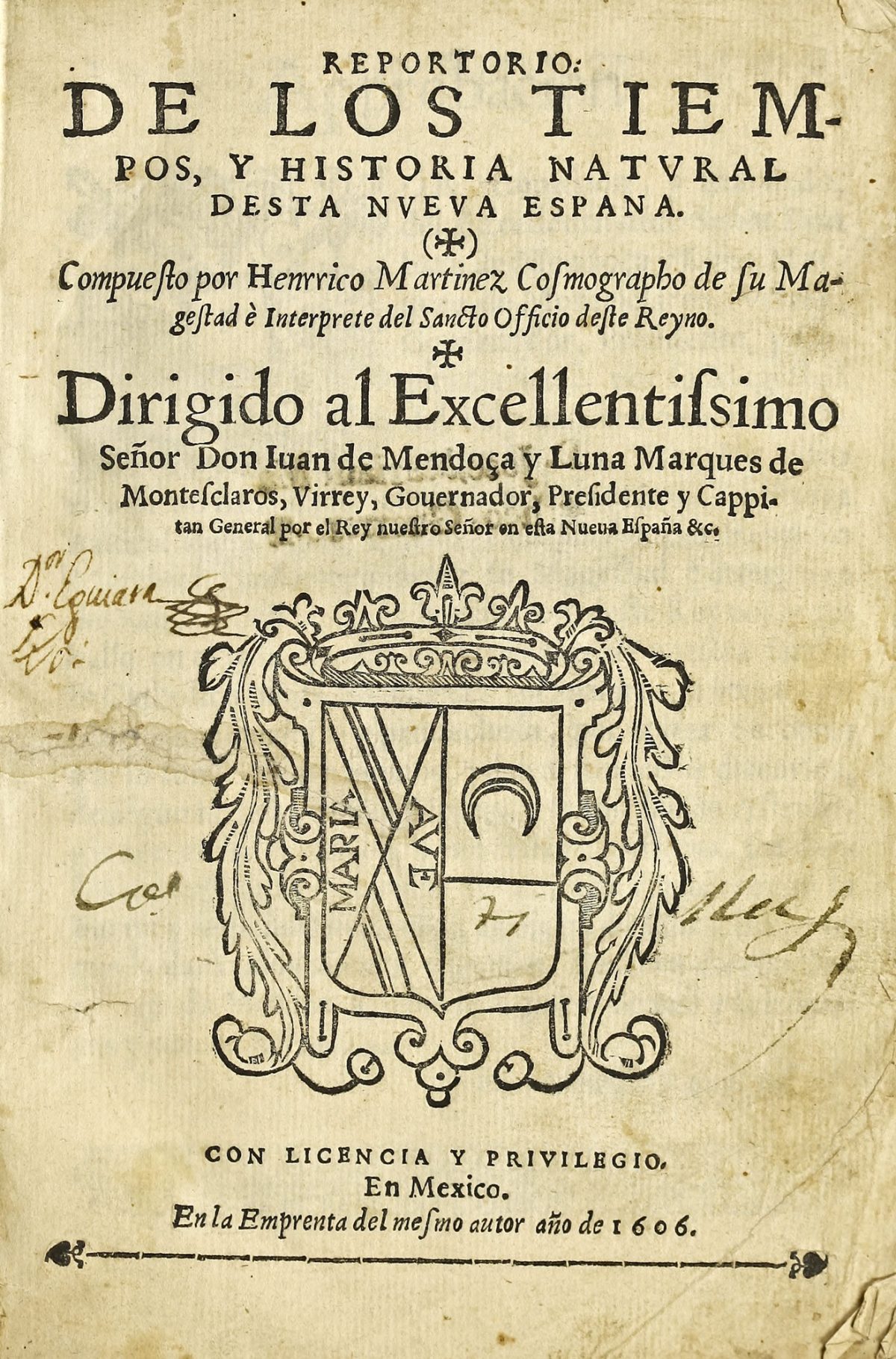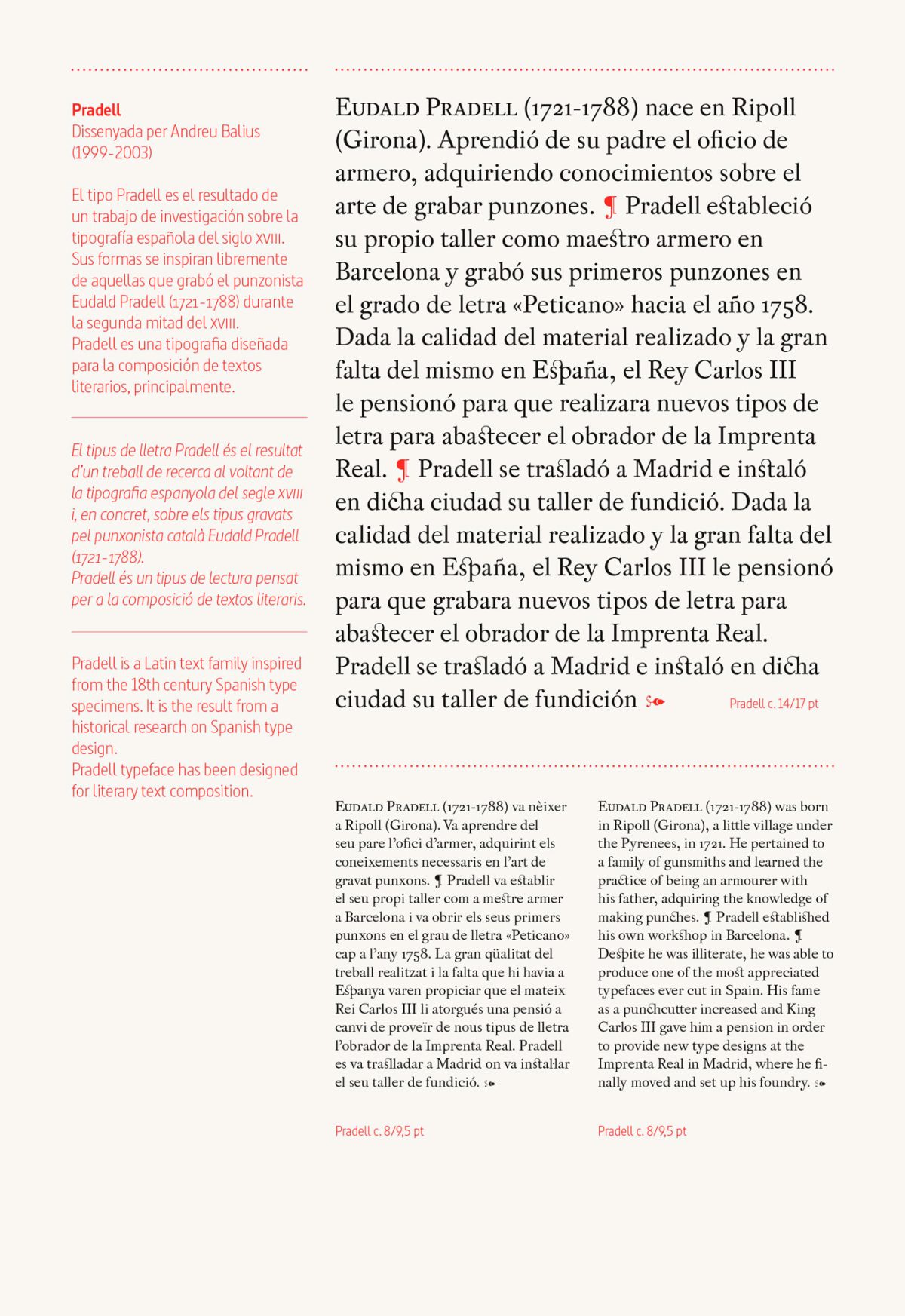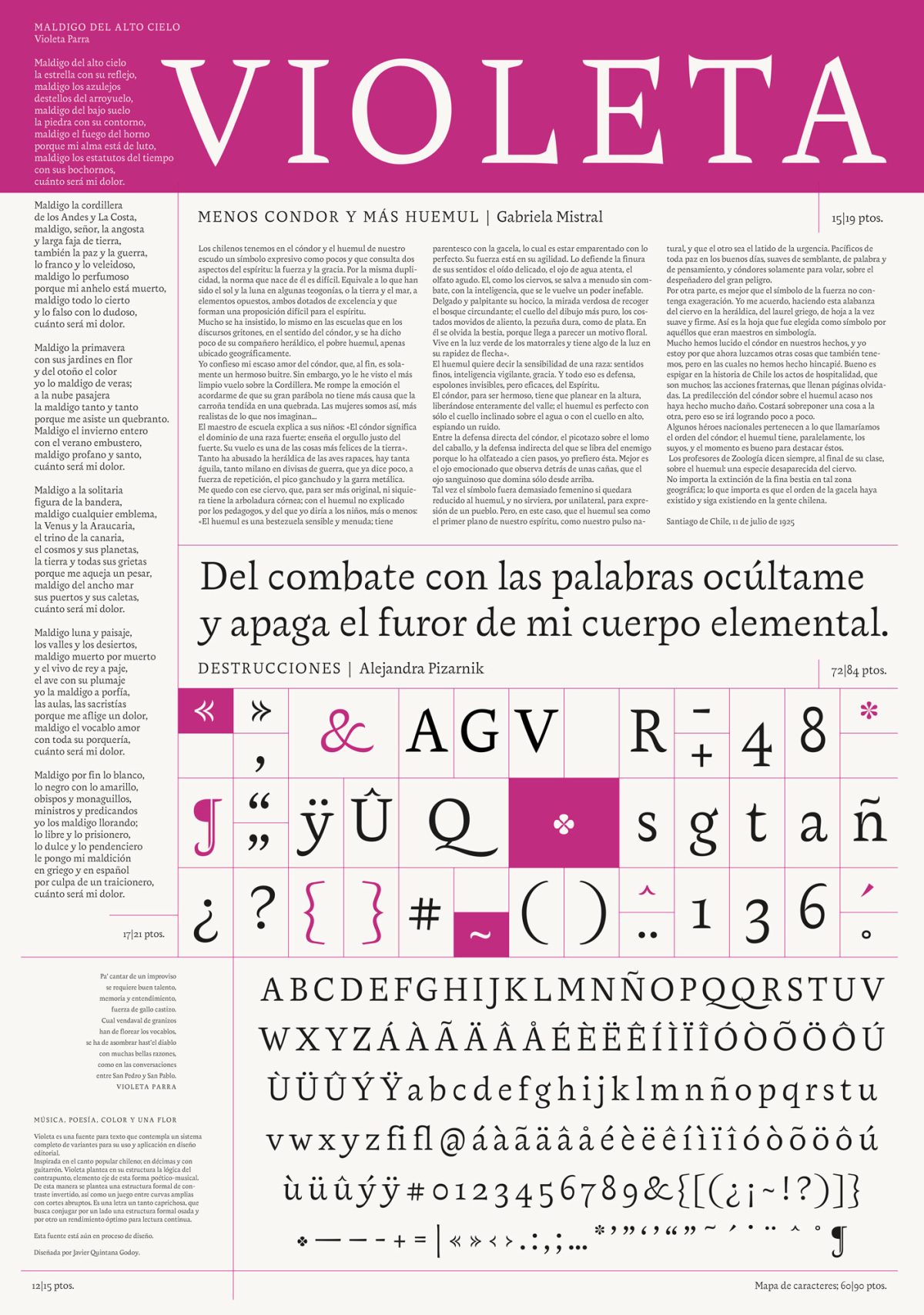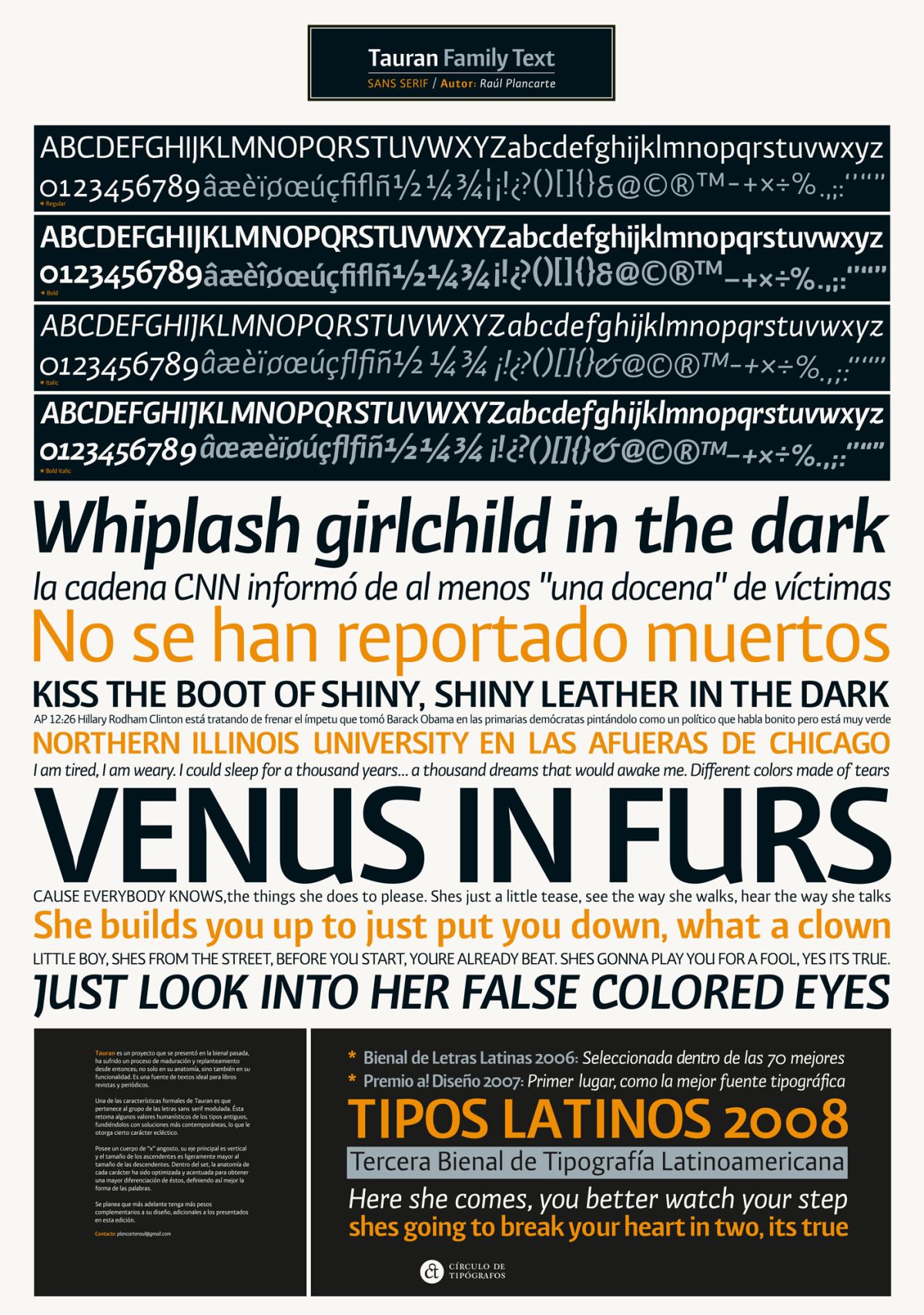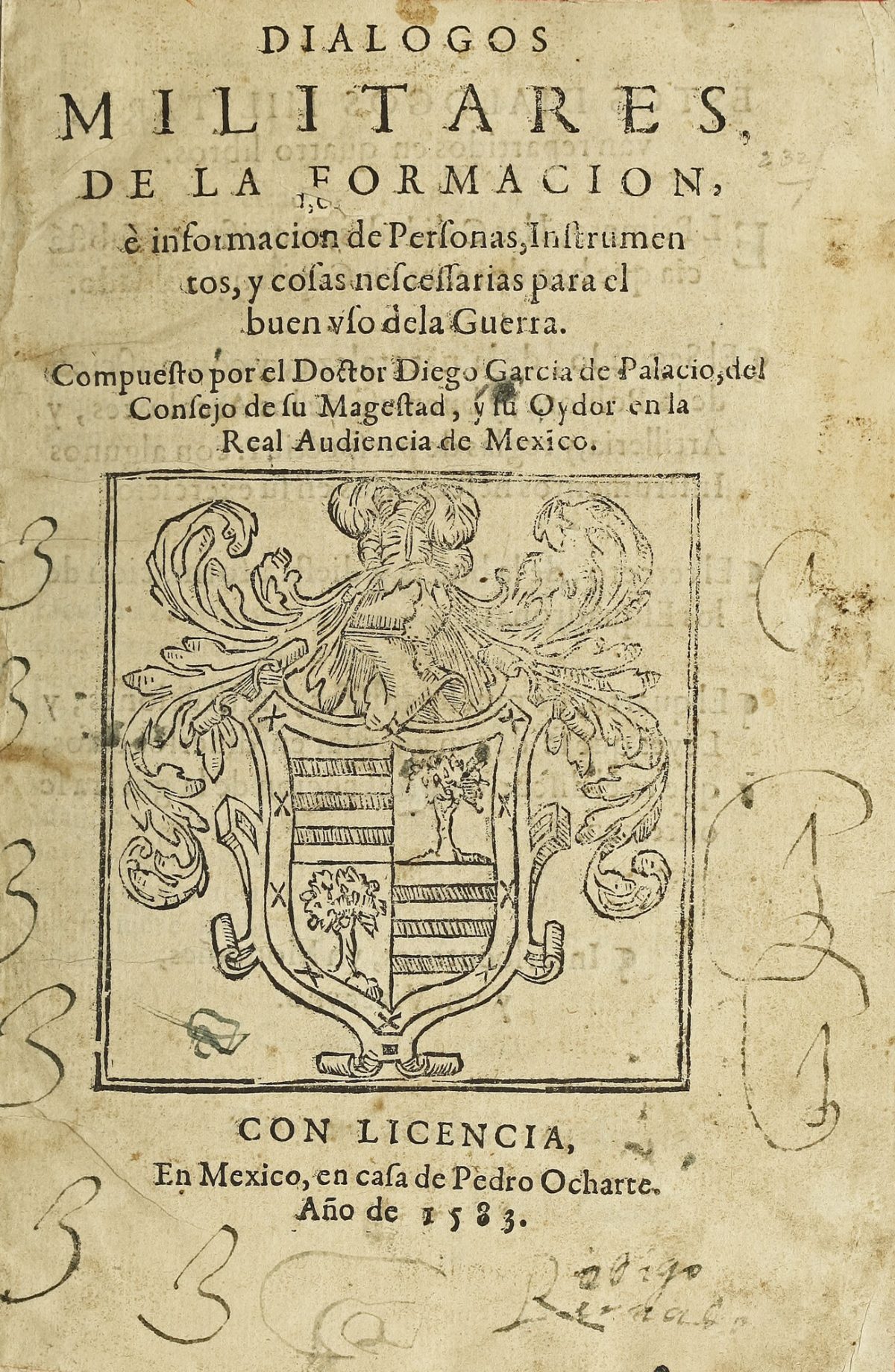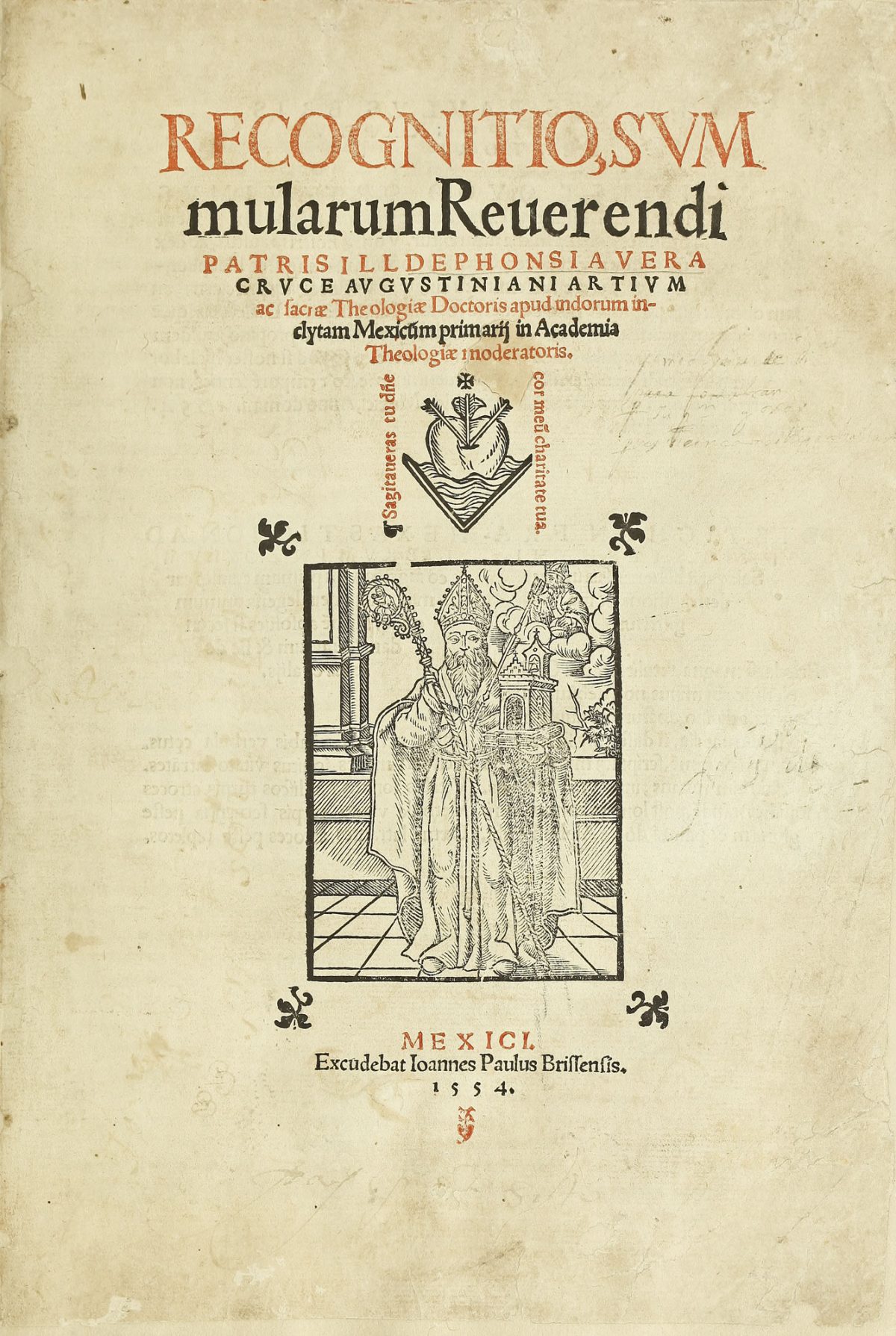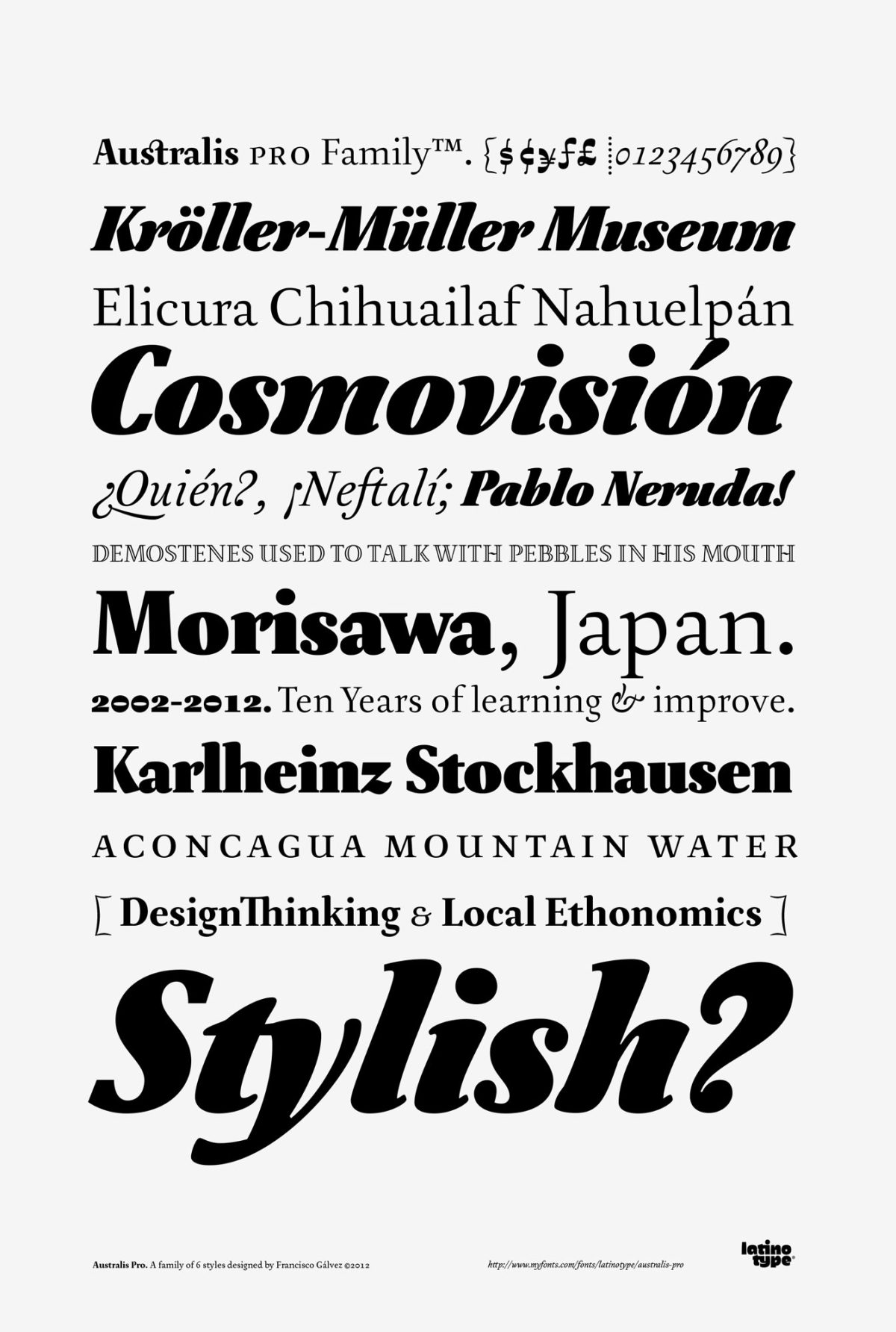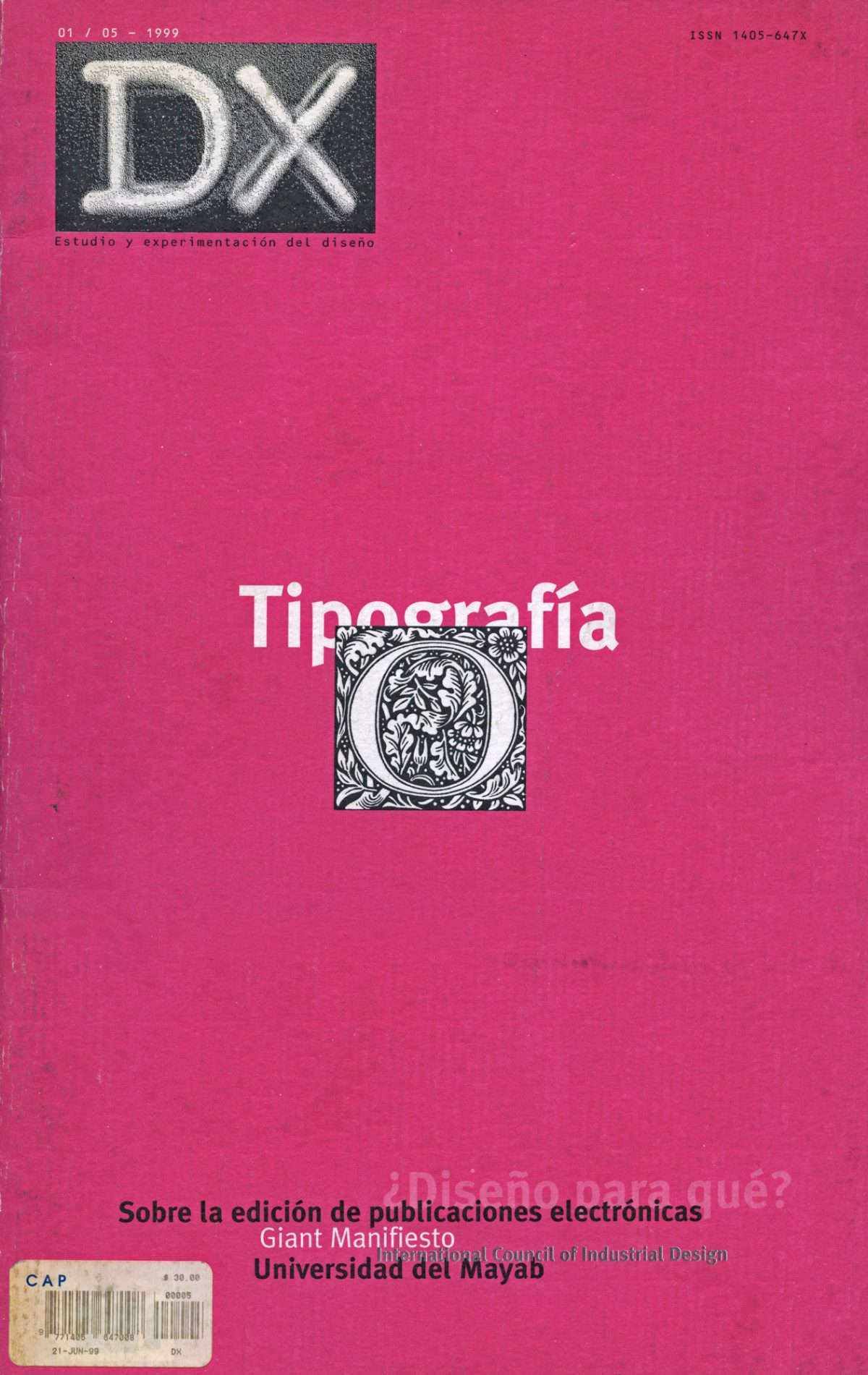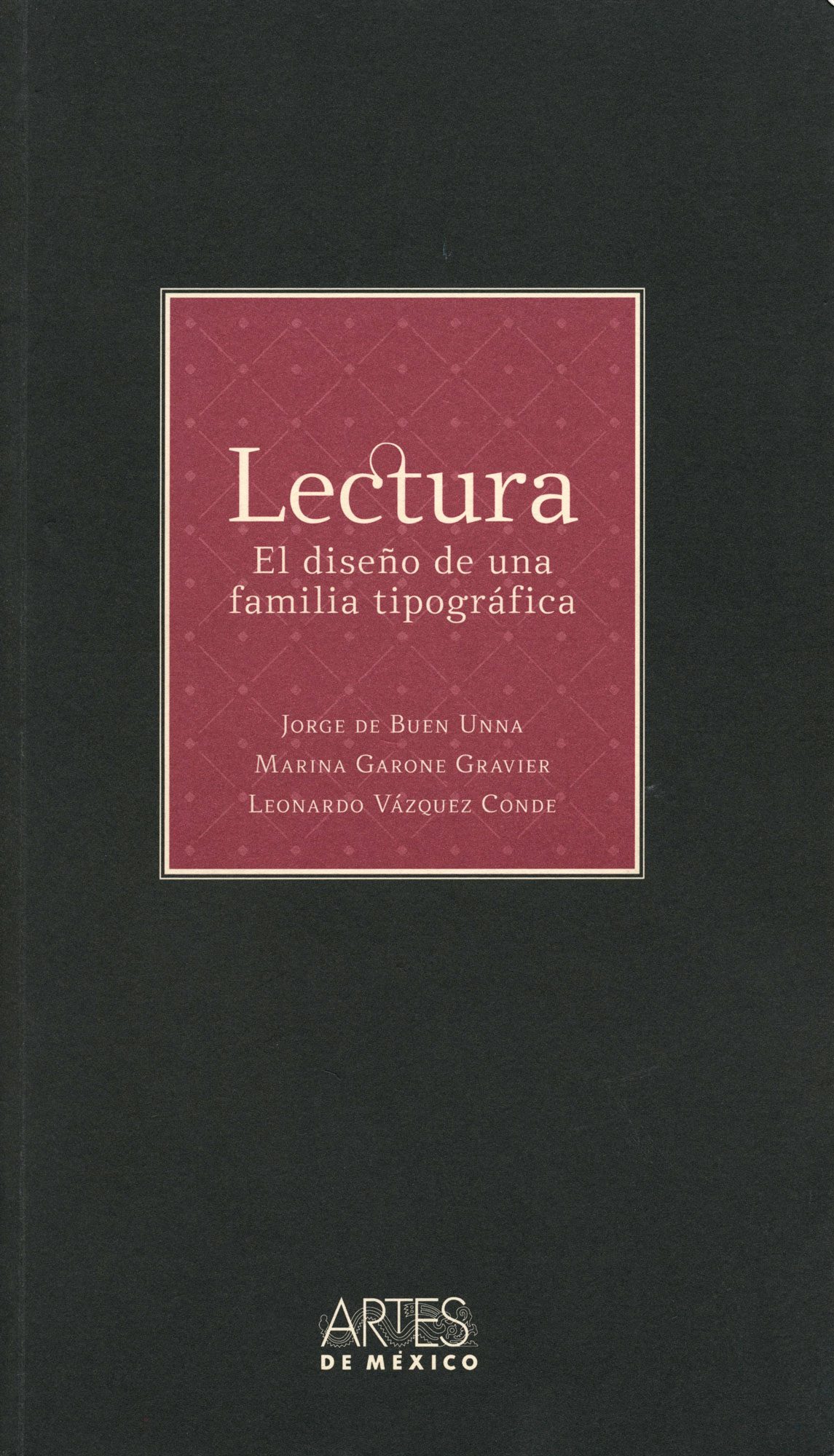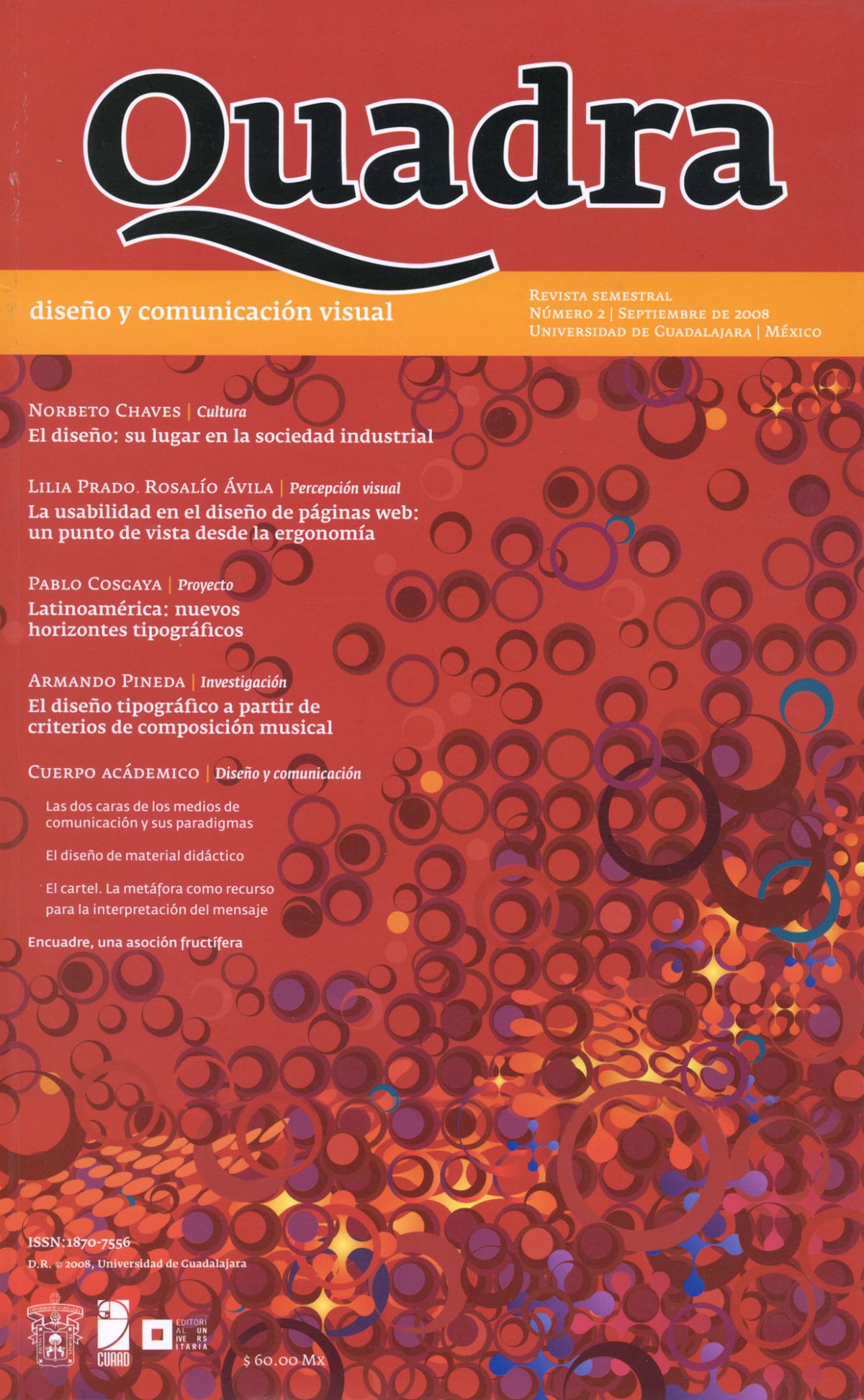
El espécimen tipográfico. ¿Herramienta de trabajo u objeto de placer? [Parte III]
El universo de la tipografía está lleno de sutilezas y detalles, de formas que transmiten ideologías a través de sus trazos. El espécimen tipográfico es el mundo que antecede a la puesta en página y donde sobran pretextos para observar el color de la trama, el contraste, el espacio entre las líneas y las letras; es el lugar donde se originan las combinaciones infinitas de los signos que esperan inertes y que aún no toman sentido en un discurso, pero que son para disfrutarse. Esta reflexión pretende esbozar el vasto mundo de una herramienta tan importante, poco recurrida y bastante desaprovechada en nuestros días. Para entenderla, es preciso conocer sus orígenes y el desarrollo que tuvo en las distintas épocas. (Tercera y última entrega del texto.)
La consolidación de la tipografía latinoamericana
La tipografía latinoamericana tuvo su origen con los primeros impresores llegados a la Nueva España para cubrir la demanda de la producción de textos. El primero fue el sevillano Antonio de Espinosa (imagen 69), y es considerado el primer tipógrafo novohispano que incursionó en esta latitud en el tallado de letra entre 1554 y 1559 (Henestrosa: 2008, 61-65). También hay noticia de un empleado de Pedro Ocharte (imagen 70), de origen francés y llamado Juan Ortiz, quien por algunos documentos se sabe que fue fundidor de tipos y cortador de grabados en esta imprenta hacia 1560. (Griffin: s/f).
Imagen 69. Muestra del tipo romano cortado por Antonio de Espinosa [1554]. Recognitio, summularum reuerendi Patris Illdephonsi a Vera Cruce Augustiniani de Alonso de la Vera Cruz. México: Excudebat Ioannes Paulus Brissensis. Imagen tomada de: archive.org. https://goo.gl/NytJyf
Imagen 70. Muestra de los tipos cortados por Juan Ortiz [ca. 1570]. Dialogos militares : de la formacion, è informacion de personas, instrumentos, y cosas necessarias para el buen vso de la guerra de Diego García de Palacio. México: casa de Pedro Ocharte, 1583. Imagen tomada de archive.org. https://goo.gl/43b9JV
Otro no menos importante fue el alemán Henrich Martin (Enrico Martínez, imagen 71) llegado en 1589 y designado cosmógrafo real y que también talló varias fuentes (Segovia: 2001, 65-77). No es de extrañarse que no se supiera de más abridores de punzones en la Nueva España —sino hasta el siglo XVIII—, ya que el material y los insumos estaban regidos por la Corona española y los monopolios de comercio europeos. Sin embargo, en el primer cuarto del siglo XX, el pintor y grabador Francisco Díaz de León fundó en México el Instituto tipográfico.
Imagen 71. Muestra de los tipos cortados por Enrico Martínez [ca. 1600]. Reportorio de los tiempos, y historia natvral desta Nveva España. México: Henrico Martinez cosmographo de su Magestad è Interprete del Sancto Officio deste Reyno, 1606. Imagen tomada de: archive.org. https://goo.gl/8rS3ks
Hacia fines del siglo XX, la creciente necesidad de investigar, teorizar y consolidar la disciplina fue la base de una corriente académica que buscó formar profesionales expertos en el tema: la introducción de programas de profesionalización como el ANRT, Atelier National de Recherche Typographique (1985), priumero en París y más tarde en Nancy, de la mano del ministerio de cultura francés; el Master Type and Media de la Real Academia de Artes de La Haya (1996); el MA en Typeface Design de la Universidad de Reading (1999), Reino Unido; o la introducción del Máster en Tipografía Avanzada del Centre Universitari de Disseny i Art de Barcelona (2003). Por otra parte en América Latina la apertura del Diplomado en Tipografía del Departamento de Estudios Tipográficos de la Universidad Católica en Santiago de Chile (2003), la Maestría en Diseño Tipográfico del Centro de Estudios Gestalt para el Diseño, en el puerto de Veracruz, México (2006), y la Carrera de Especialización en Diseño de Tipografía y más tarde Maestría en Tipografía de la Universidad de Buenos Aires (2008); permitieron el acceso al oficio en Latinoamérica y también contribuyeron a la participación de los latinoamericanos en el mercado internacional con propuestas innovadoras y en general con un estilo singular.
Imagen 72. Portada de la revista TipoGráfica nº 9 [1989]. TipoGráfica. Comunicación para diseñadores, núm. 9, noviembre de 1989. Buenos Aires. Imagen de Daniel Maldonado. https://goo.gl/LNAAdx
La tipografía latinoamericana inició ese proceso de consolidación en 1985 con el lanzamiento de la revista especializada TipoGráfica. Comunicación para diseñadores (imagen 72), dirigida por Rubén Fontana, quien influyó en muchas generaciones de diseñadores al abordar el tema desde un punto de vista más sustentado en la reflexión.
Desde un inicio la tipografía digitial latina evolucionó de forma diferente en dos latitudes: Centro y Sur. En la segunda, y evidentemente con mayor experiencia, destacaron diseñadores como Alejandro Paul (imagen 73), Alejandro Lo Celso (imagen 74), Francisco Gálvez (imagen 75), César Puertas, José Scaglione, Eduardo Manso y Eduardo Tunni (imagen 76), en cuyas manos el diseño de letra se renovó y adquirió un carácter único. Algunos de ellos han procurado la enseñanza de la tipografía en diversas latitudes y espacios académicos, además de escribir artículos sobre el tema. Al igual que en el resto del mundo suelen definirse dos perfiles más o menos claros: diseñadores de cierta versatilidad que abordan diversidad de proyectos, para texto o para rótulos, y diseñadores que se enfocan casi enteramente en un sólo género, como las fuentes script o las sanserif geométricas, géneros que suelen moverse más comercialmente.
Imagen 73. Espécimen de Steak Script [2017]. Steak Script. Diseñada por Alejandro Paul, Buenos Aires: Sudtipos, 2016. Imagen tomada de: «Steak», MyFonts.
https://goo.gl/JX6dC4
Imagen 74. Espécimen de la familia Arlt [2008]. Diseñada por Alejandro Lo Celso. Arlt. Córdoba, Argentina: PampaType font foundry, 2008. Imagen tomada de «Arlt», PampaType. https://goo.gl/Adkj1v
Imagen 75.Espécimen de la famila Australis Pro [2002-2012]. Diseñada por Francisco Gálvez. Australis Pro Family. Santiago de Chile: Latinotype, 2012. Imagen tomada de: «Australis Pro», MyFonts. https://goo.gl/dWVwAo